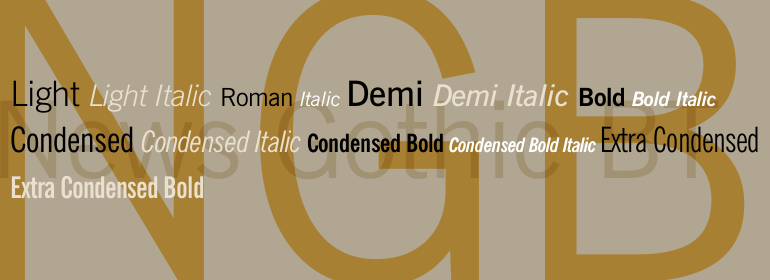
News Gothic™ BT
News Gothic™ BT,这款字体结构工整、笔画清晰,兼顾美观与易读性,适用于标题、正文、海报、包装、LOGO 等多种场景。字形优雅稳定,风格百搭耐看,适配日常排版与创意设计,让文字呈现更舒适、更具质感。News Gothic™ BT一笔一画,皆是细节,以均衡的比例、流畅的线条打造舒适视觉体验,字形端正大气,风格简约现代。无论是商业设计、品牌宣传还是日常排版,都能轻松驾驭,让文字更有格调与力量。News Gothic™ BT字体下载。
字体品牌: Bitstream(Monotype) 设计师:Benton,Morris Fuller 字体分类:无衬线体 字体属性:外文 字符集:Unicode 发布时间: 2018